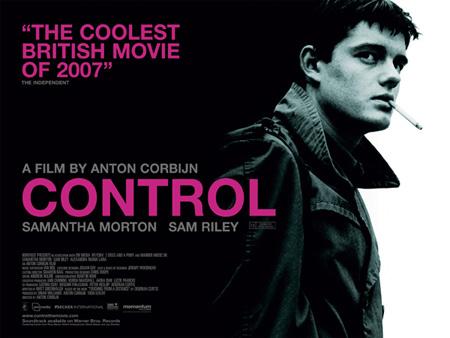
Grotesk gesucht (Film "Control" von Anton Corbijn)
AG, ja - danke.
Nur ich habe das falsche Poster gepostet, :roll: Ich wollte eigentlich diese Schriftart wissen.
Schaut mal diese Version, ein anderes "C". Wie eine Mixtur aus AG und Helvetica, oder doch eine eigene Schrift?
Es scheint ja mindestens 3 Schriftversionen für den Film zu geben. Ja, bei dir mit der Helvetica
>vielleicht gibt es auch eine version mit der TRAJAN?
Hehe, à la "when in doubt use Trajan"